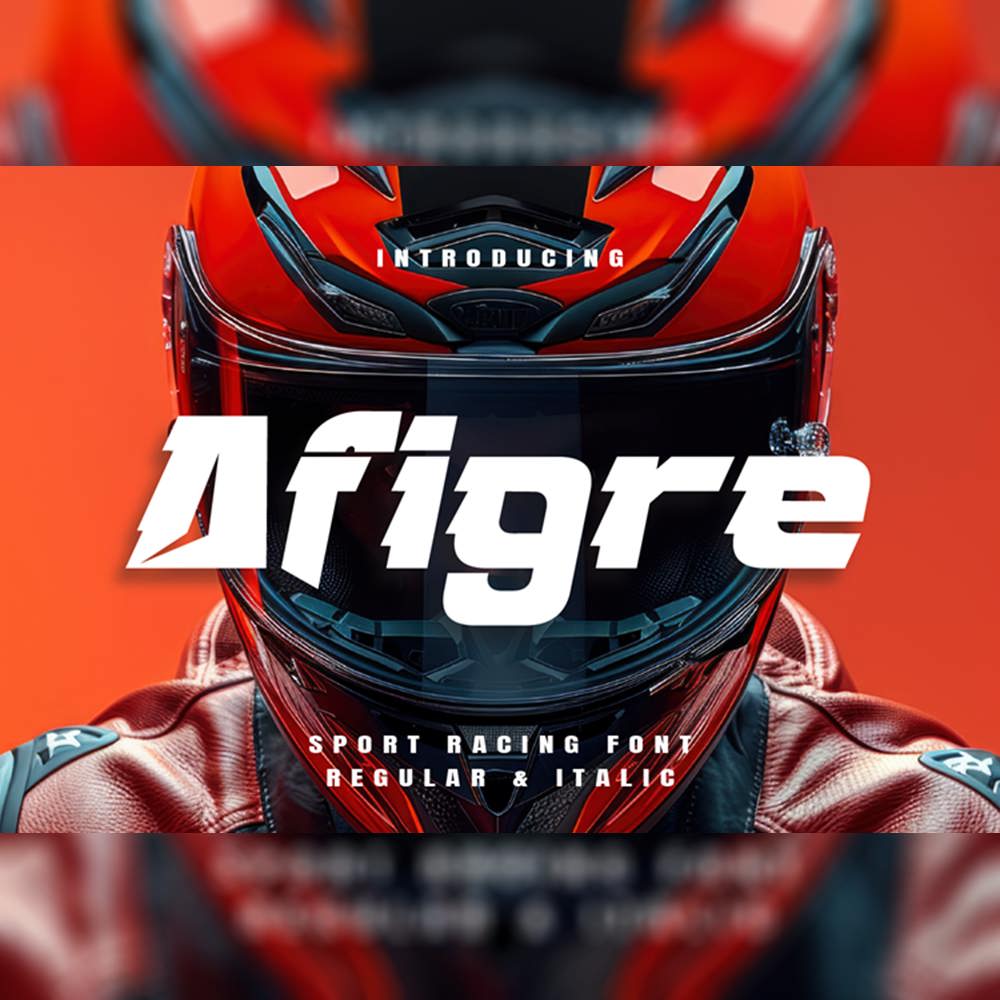
فونت پرمیوم و انگلیسی Afigre Font یک فونت نمایشی جسورانه و تهاجمی است که برای سرعت، قدرت و دقت ساخته شده است. Afigre با الهام از…
فونت پرمیوم و انگلیسی Afigre Font یک فونت نمایشی جسورانه و تهاجمی است که برای سرعت، قدرت و دقت ساخته شده است. Afigre با الهام از دنیای پرانرژی ورزشهای موتوری، برشهای تیز، زوایای مورب و فرمهای آیرودینامیکی را برای ارائه یک حضور تایپوگرافیک چشمگیر ترکیب میکند. این فونت برای پوسترهای مسابقهای، برندسازی خودرو، گرافیک ورزشهای الکترونیکی، طراحی لباس و هر پروژهای که به حال و هوای سریع و آیندهنگر نیاز دارد، عالی است.